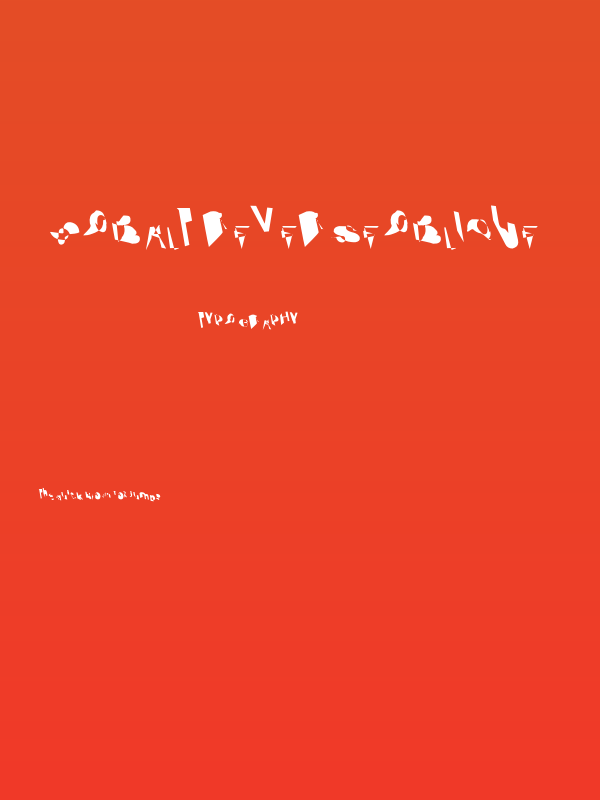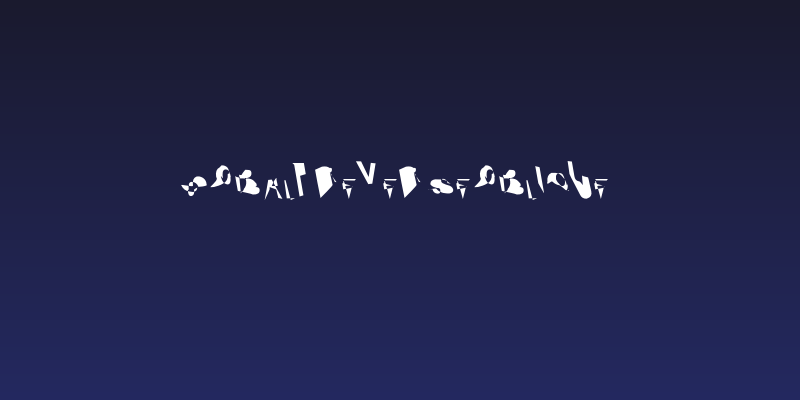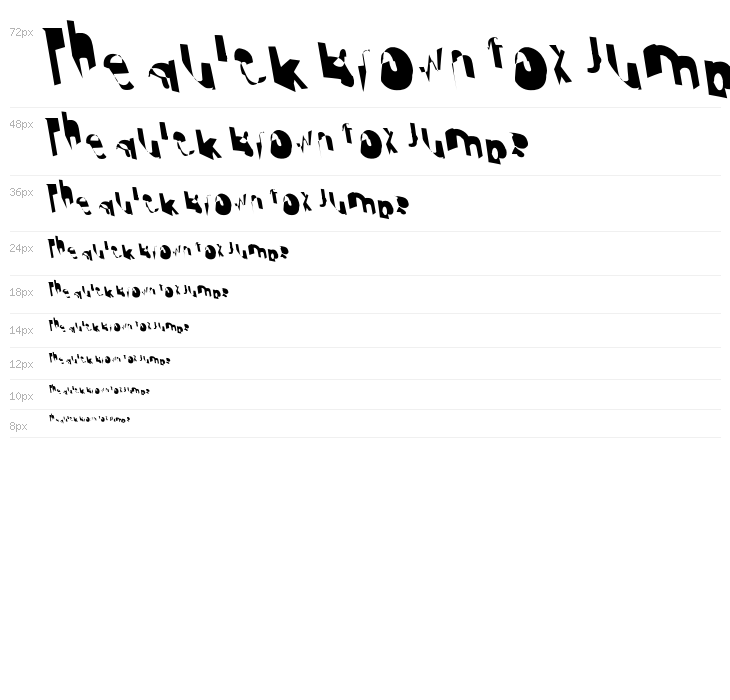
Cobalt ReverseOblique Font
✎ Distorted Eroded
| Categorie | Distorted Eroded |
| Stile generale | Modern, Avant-garde |
| Caso d'uso | Logos, Posters, Artistic projects |
| Progetti proposti | Ideal for experimental art projects, edgy branding, album covers, and modern posters. |